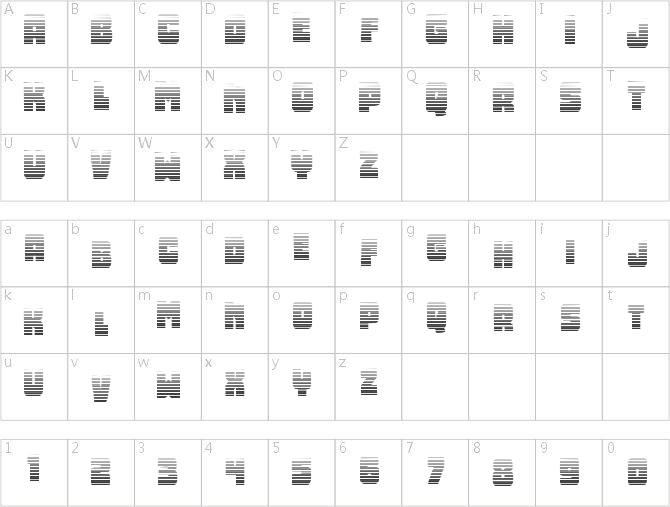
Opus Mundi Gradient 詳情頁
Opus Mundi Gradient字體字庫(kù)是一款讓人賞心悅目、百看不厭的英文字體,適合各類廣告和產(chǎn)品包裝設(shè)計(jì)應(yīng)用,字體大小0.09MB,格式為ttf字體,上傳用戶是晴朗,作者/版權(quán)方為未知